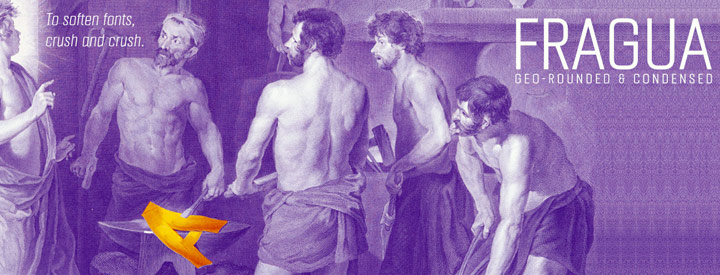
Una tipografía «Itálica» es un estilo de fuente que se caracteriza por tener una inclinación o cursiva en los caracteres. A diferencia de la tipografía regular, la versión en itálica tiene una apariencia más elegante y estilizada.
Uso de la tipografía itálica en el diseño
La tipografía itálica se utiliza para diferentes propósitos en el diseño. En primer lugar, se utiliza para destacar palabras o frases en un texto, aportando énfasis visual y jerarquía. Al enfatizar ciertas partes del texto con itálica, se crea contraste y se captura la atención del lector hacia la información relevante.
Además, la tipografía itálica también se utiliza para indicar términos extranjeros, títulos de obras, énfasis o citas. Por ejemplo, en textos académicos o publicaciones científicas, las expresiones en itálica se utilizan para resaltar nombres de especies, vocabulario técnico o palabras en otros idiomas.
Aplicaciones estéticas de la tipografía itálica
La tipografía itálica también puede añadir un toque de elegancia y sofisticación a los diseños, especialmente en proyectos de diseño editorial o branding. Se puede emplear en logotipos, tarjetas de presentación, portadas de libros o revistas, entre otros, para transmitir una sensación de estilo y distinción.
En resumen, la tipografía itálica es un estilo de fuente que se utiliza para resaltar palabras o frases, agregar énfasis y jerarquía, indicar términos extranjeros, títulos de obras o agregar un toque de elegancia a los diseños. Es una herramienta efectiva para comunicar visualmente y dar un toque especial a los textos en diversos contextos de diseño.